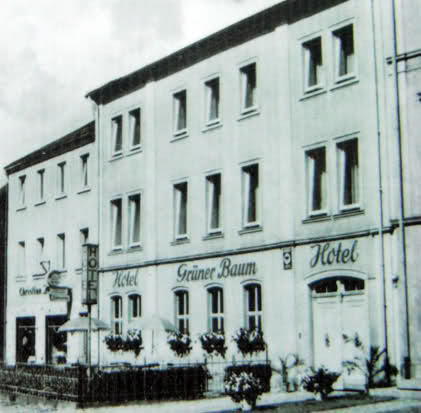
Typo für Hotel-Fassade.
heute brauche ich Eure Hilfe. Für die Neubeschriftung einer Hotel-Fassaden, suche ich den Font, der hier in den 50er Jahren verwendet wurde (siehe Foto). Mir scheint zwar, es wurde kein eindeutiger Font verwendet, sondern eher frei Hand etwas entworfen (das B, das G und das H passen m.E. nicht wirklich zusammen), aber vielleicht habt Ihr ja einen Tipp, welcher Font annähernd an das Original heran reicht. Mir geht es vor allem um das Wort "Hotel". Das schöne große "H" z.B., konnte ich in der Form auf keiner Font-Seite finden.
Habt Ihr ansonsten einen Tipp, welcher Font auch schön wäre? Klassisch, aber trotzdem zeitgemäss?
Nicht ganz, aber schon mal die Stilrichtung:
Dieses scheinbar zu hoch stehende G auf dem Photo kommt mir auch bekannt vor; vielleicht gibt es das ja doch als Satzschrift.
[specimen=Hotel Grüne Soße:zxddee87]41685[/specimen:zxddee87] ist etwa die Richtung.
Die Nuptial hat dieses seltsame hochgestellte G, auch wenn sie sonst nicht paßt:
Auch nur eine weitere Variante, die Monotype Script passt also doch wohl noch am ehesten: